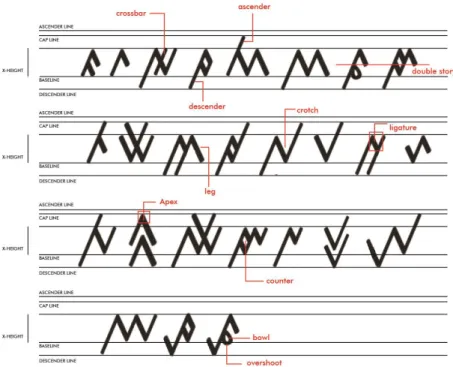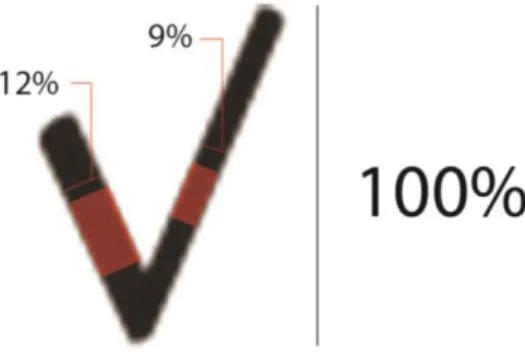
BAB III
METODOLOGI
3.1. Metode Pengumpulan Data
Metode pengumpulan data menurut Yusuf (2014), dapat dibagi menjadi dua bagian, yaitu metode kuantitatif dan kualitatif. Untuk teknik pengumpulan data kualitatif adalah dengan wawancara dan observasi. Perancangan ini menggunakan metode kualitatif disertai dengan foto dokumentasi lapangan dan narasumber. Selain itu, metode lain yang digunakan adalah studi referensi.
3.1.1. Wawancara
Menurut Yusuf (2014), wawancara atau interview adalah teknik atau proses interaksi antara pewawancara dan sumber informasi (hlm. 372-376). Ada beberapa narasumber ahli yang memahami tipografi dan Aksara Kaganga. Narasumber pertama adalah Andy Aw. Masry sebagai type designer Indonesia yang memiliki type foundry, Campotype, dan diakui oleh Linotype dan MyFonts. Narasumber kedua adalah Ahmad Rapanie Igama sebagai filolog yang ahli dalam Aksara Kaganga dan Naskah Surat Ulu. Narasumber ketiga adalah Wahyu Rizky Andhifani yang juga meneliti Aksara Kaganga dan Naskah Surat Ulu di Balai Arkeologi Sumatera Selatan. Narasumber keempat adalah Samsudin, bagian dari koleksi dan konservasi Museum Negeri Sumatera Selatan, yang memahami tentang Aksara Kaganga dan Naskah Surat Ulu. Narasumber terakhir adalah Alanna Munro, salah satu type designer asal
53 Columbia, Inggris. Munro merupakan type designer dari type foundry bernama LostType.
3.1.1.1. Wawancara dengan Andi Aw. Masry
Andi Masry adalah type designer asal Makassar yang menjalankan type foundry, Campotype, dan diakui oleh Linotype dan My Fonts. Andi Masry telah mengenal tipografi sejak dari kecil dan mulai mendesain font sejak tahun 2008. Wawancara dilakukan melalui e-mail, dengan mengirimkan beberapa pertanyaan pada tanggal 29 Agustus 2018, karena perbedaan lokasi.
Menurut Andi Masry, sumber inspirasi untuk membuat typeface bisa datang dari mana saja dan membutuhkan kejelian dalam menyikapinya dengan merumuskan inspirasi tersebut. Tetapi, tidak semuanya bisa dirumuskan menjadi ide yang bermanfaat dan memiliki efek jangka panjang. Tidak lupa Andi Masry mengingatkan bahwa pentingnya sebuah riset dilakukan untuk menjadikan rumusan ide tersebut ke dalam proses eksekusi dalam perancangan typeface. Andi Masry menambahkan bahwa ada beberapa aspek yang perlu diperhatikan dalam merancang typeface. Pertama, huruf sebagai “pakaian bahasa” bisa disebut sebagai salah satu elemen utama dalam komunikasi, karena itu sangat penting merancang huruf semaksimal mungkin sehingga memenuhi fungsinya dengan baik sebagai sarana
54 komunikasi. Kemudian, orisinalitas, penyederhanaan bentuk, dan legibility serta readability.
Pendapat Andi Masry tentang typeface bermuatan lokal, seperti adaptasi dari aksara sangat baik dan diperlukan. Tetapi perlu diingat bahwa tujuan utamanya adalah merancang typeface yang fungsional, sehingga budaya lokal ini harus melalui proses interpretasi esensi dari budaya tersebut untuk dapat diimplementasikan dalam typeface. Menurut Andi, kita tidak sekedar menggambar huruf, melainkan membuat huruf yang bisa bekerja di dalam kata dan kalimat. Kurangnya interpretasi pada proses ini, dimana desainer hanya melakukan re-capturing budaya lokal tertentu, hanya akan menyebabkan hasil desain yang kaku dan kurang fungsional. Maka dibutuhkan alat interpretasi yang banyak, bisa dari bentuk fisik, keunikan, filosofi, sejarah, ikon budaya lainnya dari daerah yang sama (misalnya ornament lokal) dan sebagainya. Semuanya itu bisa digabungkan dengan prinsip desain modern. Terakhir, Andi Masry berpendapat bahwa industri typeface dan type designer Indonesia akan berkembang jika ada kesadaran akan pentingnya typeface sebagai kekayaan intelektual, terutama dalam budaya lokal.
3.1.1.2. Wawancara dengan Alanna Munro
Alanna Munro merupakan type designer asal Columbia, Inggris yang menjadi salah satu type designer di type foundry bernama LostType. Munro
55 juga membantu salah satu komunitas pertemuan type designer bernama Type Brigade. Wawancara dilakukan melalui e-mail dan direspon pada tanggal 20 September 2018.
Munro mengatakan bahwa ide dan gagasan untuk melakukan perancangan sebuah typeface didapatkan dari melakukan sebuah penelitian. Menurutnya, ide dari sesuatu yang bersejarah membuat perancangan typeface menjadi lebih menarik. Setiap teknik dalam proses perancangan typeface sangat penting, terutama ketelitian dalam spacing, pengulangan bentuk, dan teknik menggambar typeface, sehingga typeface tersebut dapat digunakan secara tepat oleh desainer dalam meningkatkan kualitas karya mereka.
Menurut Munro, bahwa type industry sudah mulai berkembang. Perkembangan ini dilihat dari sudah banyak informasi-informasi secara online yang dapat ditemukan dan dipelajari siapapun secara mandiri. Hal ini membuat type designer menjadi berkembang dalam membuat suatu karya. 3.1.1.3. Wawancara dengan Ahmad Rapanie Igama
Ahmad Rapanie Igama merupakan filolog, seseorang yang mempelajari bahasa dan sumber sejarah yang ditulis, yang mendalami Aksara Kaganga dan Naskah Surat Ulu, yang bekerja di Dinas Kebudayaan dan Pariwisata Provinsi Sumatera Selatan. Wawancara dilakukan pada tanggal 10
56 September 2018 di Kantor Dinas Kebudayaan dan Pariwisatan Provinsi Sumatera Selatan di Kota Palembang.
Rapanie mengatakan bahwa Aksara Kaganga merupakan aksara proto-Sumatera yang berkembang dari Aksara Pallawa dan bahasa Melayu, yang kemudian digunakan oleh masyarakat bagian ulu sesuai dengan keperluan mereka sendiri. Aksara Kaganga ini kemudian berkembang di daerah lainnya, diluar Sumatera Selatan, seperti Bengkulu, Jambi, dan Lampung. Bentuk dari Aksara Kaganga yang kaku disebabkan oleh media tulis awal, seperti bambu dan tanduk. Berdasarkan penelitian beliau, Aksara Kaganga ini berkembang pada masa transisi antara Kerajaan Sriwijaya menuju Kesultanan Palembang sehingga ada beberapa naskah yang bercerita tentang masuknya agama Islam di Sumatera Selatan. Masyarakat menggunakan Aksara Kaganga ini sebagai alat komunikasi, pengajaran, dan ekspresi. Tetapi, fungsi utamanya adalah mewariskan kebudayaan.
Rapanie menambahkan penggunaan Aksara Kaganga yang berwujud nyata sampai sekarang adalah Naskah Surat Ulu, sehingga naskah ini dapat menjadi dasar untuk mempelajari dan meneliti Aksara Kaganga. Naskah ini banyak ditemukan di daerah Pagaralam, Lahat, dan Oku, Sumatera Selatan. Tetapi, ada beberapa naskah yang masih dimiliki masyarakat setempat dan dijadikan benda keramat karena merupakan pusaka keluarga, sehingga tidak boleh dibaca, ditulis ulang, bahkan disentuh. Beliau
Mempertimbangkan ruang antar huruf sama pentingnya merancang bentuk huruf. Banyaknya karakter dalam typeface menentukan ukuran ruang antar huruf, sehingga setiap pasangan huruf bisa memiliki ukuran ruang huruf yang berbeda, misalnya pada AV dan Ya.
3.2.10. Setting Text
Setelah perancangan selesai, diperlukan pemeriksaan hasil dari typeface yang sudah dibuat untuk memeriksa ukuran jarak dan proporsi. Hal ini bisa
84 dilakukan dengan melihat hasil print test dan menggunakan metode pangram, seperti pada kalimat “The Quick Brown Fox Jumps Over the Lazy Dog”.